32 个最佳免费迪士尼字体集
已发表: 2022-06-30华特迪士尼成功地创造了这个吸引儿童和成人的神奇世界,这体现在今天这个庞大的全球品牌中。
由于带有迪士尼印记的各种主题公园、电视节目、电影和电子游戏,它已经渗透到人们生活的方方面面。
因此,迪士尼精心制作的印刷字体列表对数字设计行业产生了重大影响也就不足为奇了。
这些印刷字体大量借鉴了迪士尼的性质和内容,并进行了相应的设计以散发故事或其世界的理念。
我们汇总了 30 种最佳迪士尼字体列表,您可以有效地使用它们的复杂性和精致性。
米奇
一个漂亮的漫画形式,非常适合与孩子相关的各种项目以及任何其他应该活泼有趣的项目。 这种漫画风格的字体非常适合儿童海报、传单儿童读物、卡通和相关的 ptojects。
它提供大写、小写、数字等。
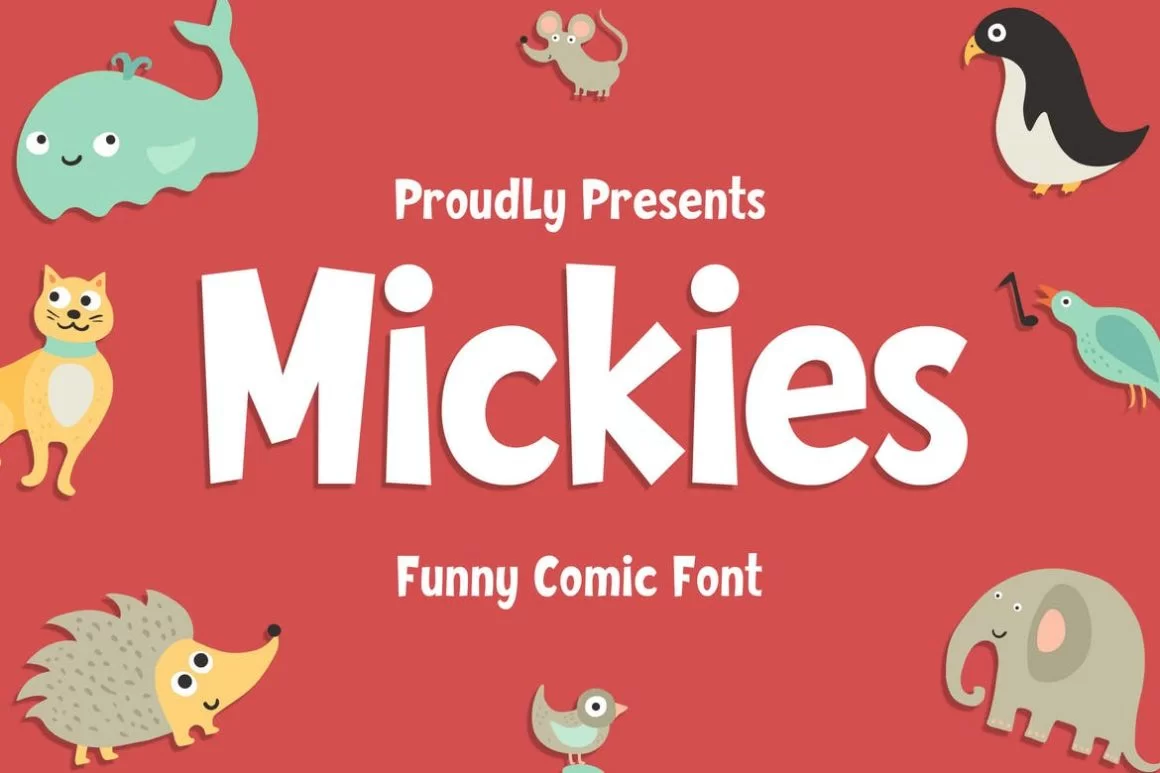
复仇者
你是复仇者联盟的粉丝吗? 如果是这样,这里的字体会让你开心。 Avenger 的标志使它有别于其他类似的项目,它本身就是一个品牌,你可以在你的项目中使用类似的字体来展示你对这部流行电影的热爱。
您可以使用字体并使其正常,斜体,粗体和粗斜体。
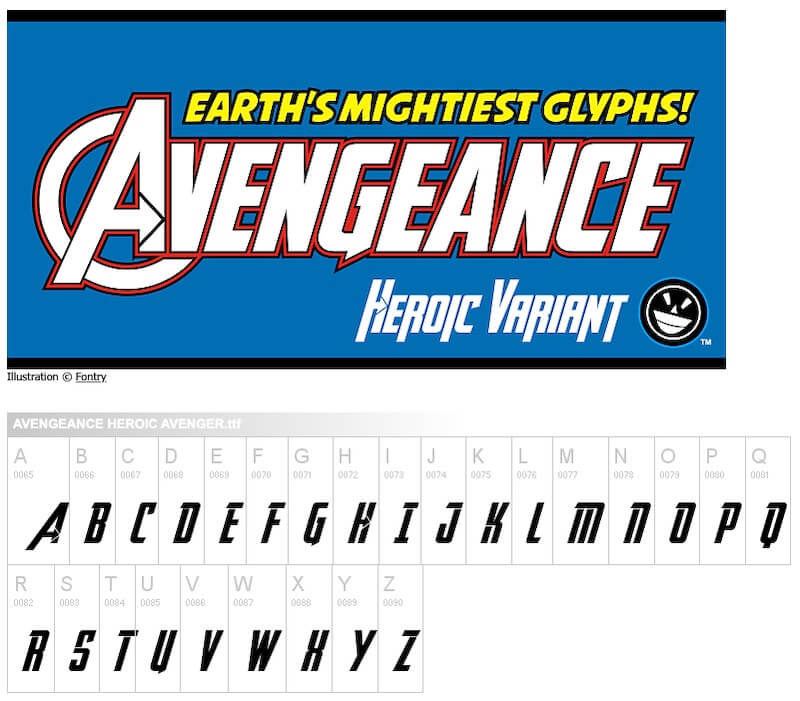
爱丽丝漫游仙境
我敢肯定你知道爱丽丝梦游仙境,一个非常受孩子们欢迎的故事。 这是一款受爱丽丝梦游仙境电影启发的字体。
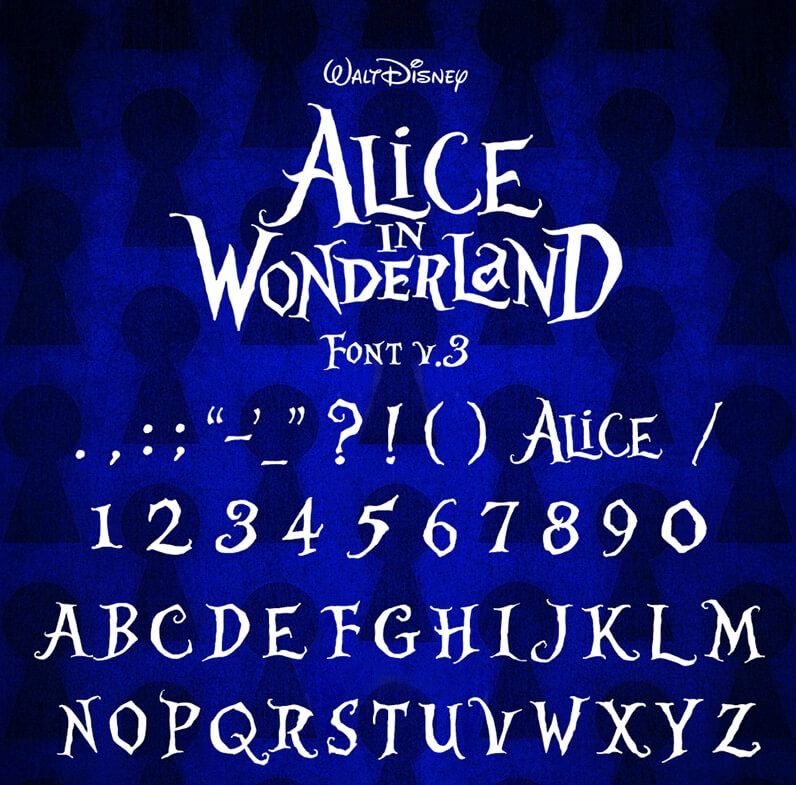
鼠标回忆录字体
反映了家喻户晓的名字和原始人物米老鼠的形象,这种字体的滑稽笔触大胆而幼稚粗暴和异想天开。
据说它也受到了 1950 年代唐老鸭和高飞角色的启发。
包含纯粹的乐趣,当您的目标受众是儿童或幼儿时,这种字体是理想的。
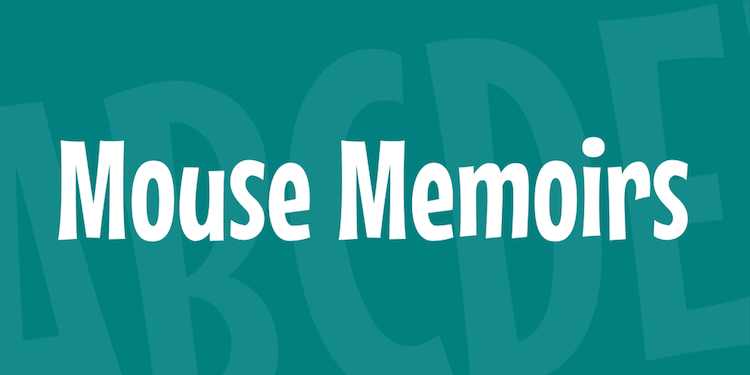
米奇耳朵字体
米老鼠的圆形黑色耳朵是迪斯尼的标志性符号,更能看到孩子和成人都戴着耳朵或米奇和米妮。
这种字体主要是图形的,每个字母都包裹在米奇耳朵的黑色轮廓中。
虽然相当吸引人,但这种字体仅适用于大写字母,更适合需要注意的小标题或单词。
纠结
长发公主臭名昭著的故事被重述为弗林和长发公主之一,电影《魔发奇缘》大胆地启发了这种字体。
这种字体采用大胆的金色装饰,应该反映长发公主的金色鬃毛,非常适合挂在墙上的生日横幅和彩色字母。
它优雅,装饰性强,笔触厚实,质感丰富。
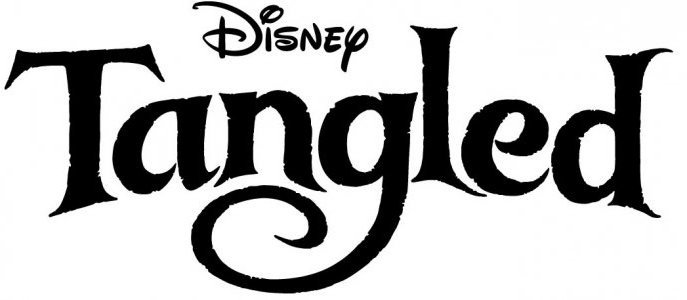
科学怪人
你会猜到下一个字体是在著名的怪物角色弗兰肯斯坦之后出现的。
这种破烂的字体应该是哥特式和怪诞的,并且不辜负着名文学的恐怖故事。
万圣节主题派对海报的理想选择,字体在大写字母中表现良好,但兼容所有尺寸。
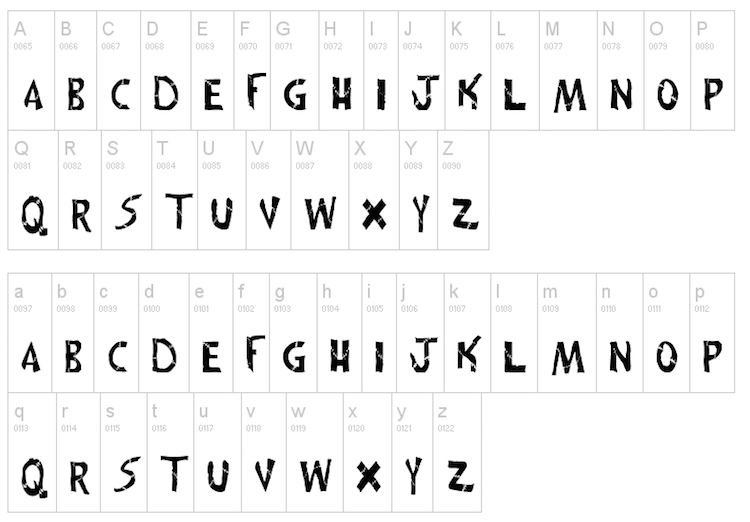
圣诞节前夜
这种特殊的字体经过精心装饰,带有扩展的字母结尾,使其看起来华丽而饱满,而不是间隔开和稀疏。
蒂姆伯顿的圣诞前夜反映了可怕和血腥,字体巧妙地融合了这些。
如果您仔细观察,您会发现字母略微弯曲,界面清晰而弯曲。
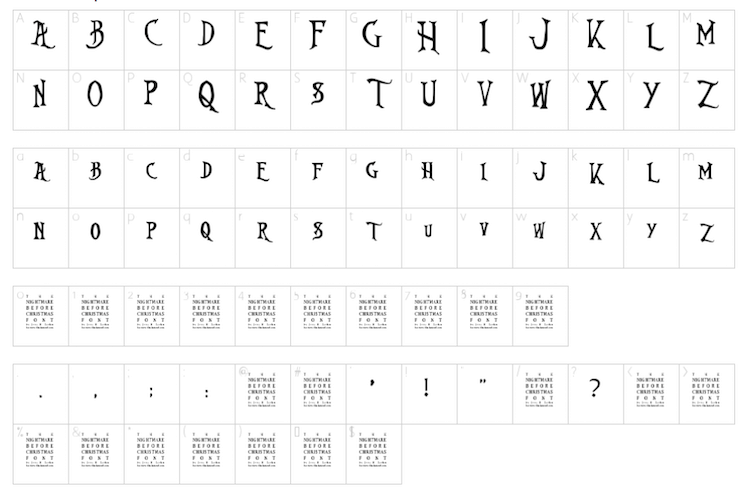
Tron Muestre Cine
作为电影杰作之一,Tron Muestre 受到了昔日一代的崇拜。
未来主义的吸引力描绘了一个技术驱动的世界的愿景,这种字体有拉长的正楷字母,带有特定色调的彩色包裹。
这专门用于为您的措辞生成 3D 吸引力,同时承载机械和机器人的提示。
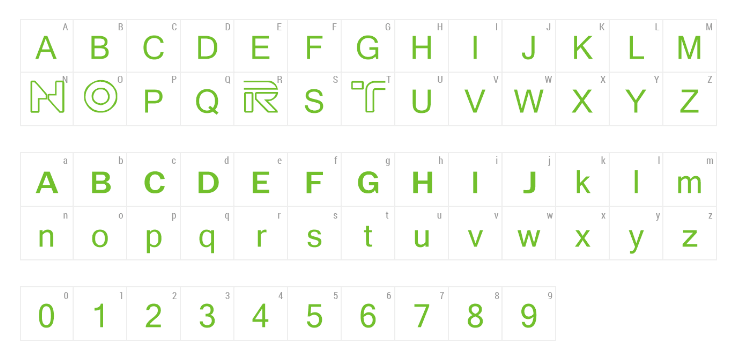
公主与青蛙
相当经典的字体,旨在唤起公主与青蛙故事的富丽堂皇和皇室。 为数不多的同时兼容大写和小写字母的迪士尼字体之一。
散发出复古而正式的外观,这种字体对于信笺或印在邀请函上是个好兆头。 字母结尾处的戏剧性和尖锐的天赋是值得注意的
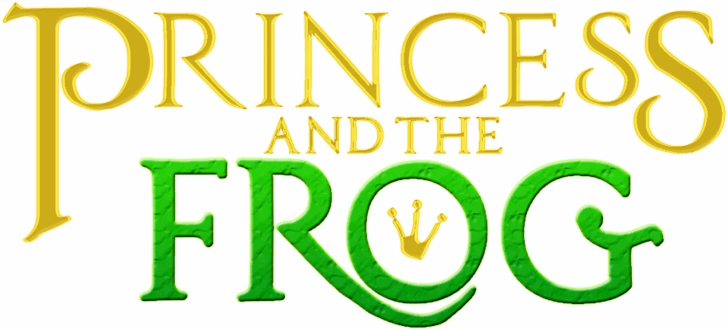
太空时代字体
对于制作《星球大战》传奇系列的公司来说,如果没有专门用于反映星际吸引力的单独字体,那是不可能的。
在这里,界面看起来垂直浓缩但宽阔,间距充足,笔触细。 为了带出完整的外太空感觉,这种字体类似于美国宇航局推广的字体
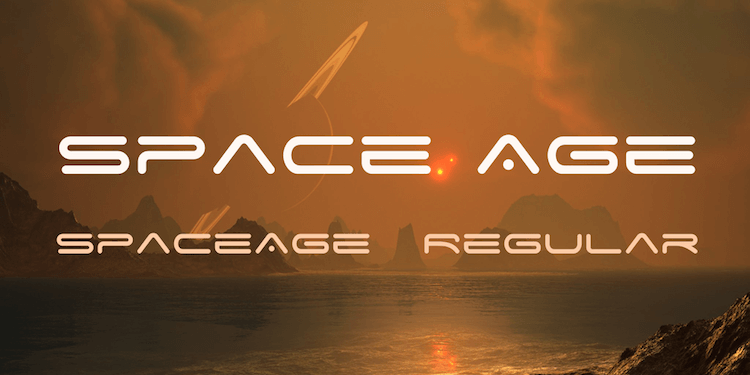
Firehouse Pup 字体
101 只斑点狗中可爱的斑点狗幼崽让每个人都心动了。 继经典电影之后,这款字体完全由小狗脸制成,字母包裹在狗项圈上。
它非常适合您的狗的生日派对或兽医标牌中的常见用途。
纳维达
在壁炉前哼着菲利克斯·纳维达 (Felix Navidad) 并在第一片雪花落在地上时喝酒,定义了真正的圣诞精神。
这种字体是关于圣诞精神的。 这种字体带有正楷字母,具有非常英式的外观,并且粗体且易于阅读。
牢记节日精神,设计师们在原本正式的信件中加入了一些古怪的元素。 这在圣诞贺卡和邀请函上看起来很可爱。
怪物公司
这是给你所有的怪物。 公司的粉丝在那里。 这种排版大胆而大,并勇敢地决定将角色 Mike Wazowski 的臭名昭著的眼睛包括在他们的一些宽泛的字母表中。
纯粹以乐趣为基础,这种字体还散发出一定的力量和热情,无疑是孩子们的最爱。
艾尔灰姑娘
灰姑娘是最受欢迎和最神奇的童话故事之一,也是大众的最爱。 Cinderella 字体是迪士尼的创始之作,具有复杂的装饰性,带有古英语草书字母和华丽的背景,每个字母都装饰着爬行动物。
优雅和精致的缩影,这种字体非常适合大写字母和小写字母。 它为您的横幅或标题增添了美感。
沃尔图
S kids 我们熟悉的著名字体之一是华特迪士尼标志。 粗线条的粗线条和环状结构。
迪士尼的品牌通常与这种字体相关联,迪士尼赞助或制作的几部电影在最初的演职员表中使用这种字体来显示他们的赞助。
原型
Prototype 看似未来派,是一种非常简单的字体,也非常引人注目。 它的方形结构非常类似于科幻电影中使用的计算机字体。 它垂直直立,自然大胆,末端略微弯曲。
这种字体间距很大,非常适合标题的标题。 它粗壮的吸引力使它很容易引人注目。
布拉德利免费
Bradley Gartis是一部古英语文本,它的诞生可以追溯到 19 世纪。 自从数字化以来,它经常与复古的哥特式字体联系在一起。 它是精致、实用和接壤的书法。
在这种字体中识别出的强大灵巧笔画是一个完美的标题或标题,同时也适用于小字体。
塞尔兹尼克 NF
Selznick BF 系列大致基于 ITC Anna 字体。 最新包含小写字母,这种字体是粗体和直立的。 虽然很滑稽,但这种字体具有某种权威。
略微弯曲、细长和压缩的字母在大写和小写中同样适用; 使其越来越多才多艺。
佛罗里达项目一期